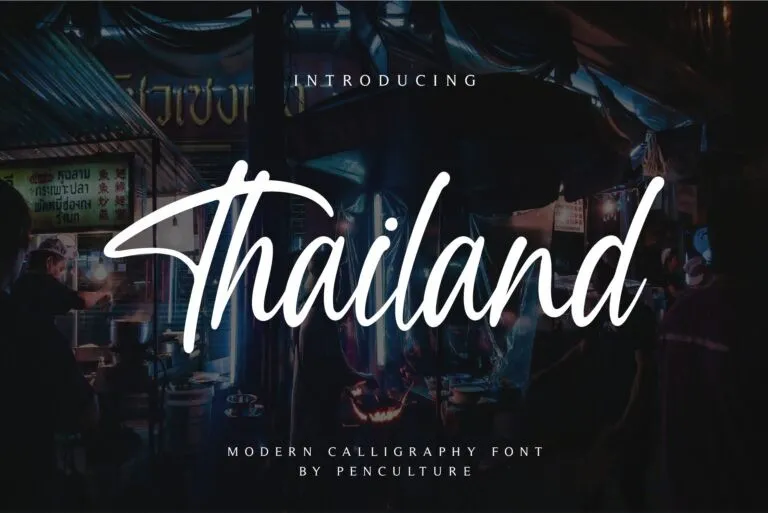
Thailand Font – Fonte Grátis
Thailand Font
A Thailand Font é uma elegante escolha para aqueles que procuram um tipo de script envolventemente bonito e fluiu naturalmente. Desenvolvida pela Pen Culture, esta fonte representa a tranquilidade e a fluidez de letras ditas à mão, ideal para o seu grande dia. É perfeita tanto para usar em sua cerimônia matrimonial como também se adequa a uma variedade de projetos gráficos, como logotipos, convites para eventos especiais, citações, embalagens de produtos, designs de marca e títulos de capas de livros. A Thailand Font também é uma opção ideal para jogos com nomes criativos ou até mesmo designs mais leves e alegres, tudo isso sem perder a elegância e sofisticação que este tipo de font oferece. Se você busca um estilo elegante e envolvente para seus projetos gráficos, a Thailand Font é uma ótima escolha.